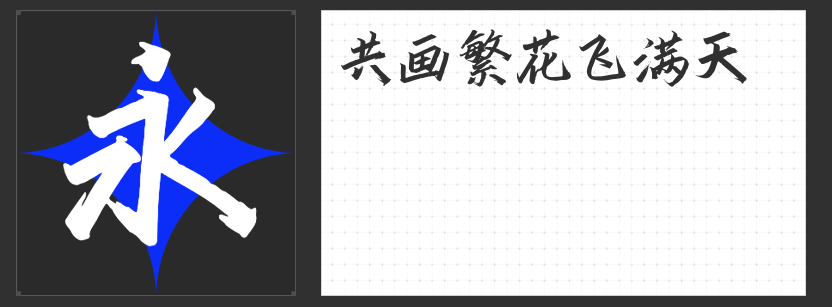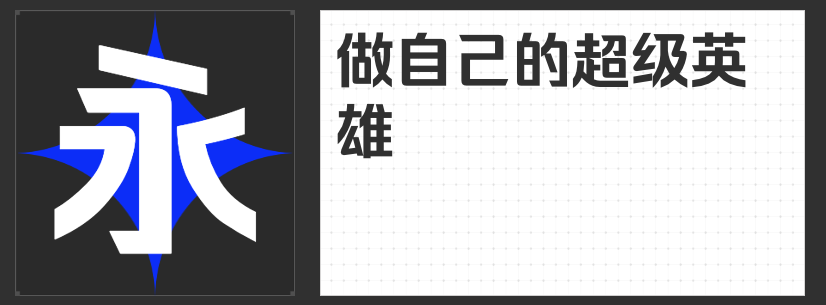
四款电商设计“吸睛利器”字体推荐~为设计施加视觉魔法
电商设计需在短短几秒内抓住用户注意力,字体作为视觉核心元素,直接影响品牌调性与转化率。本文精选四款风格迥异的商业字体,涵盖国风书法、现代黑体、实验性斜体及呆萌手绘风,助你轻松打造差异化视觉体验。
一、造字侠今朝醉简
这款毛笔楷书字体以“醉酒挥毫”为灵感,收笔处凌厉飞白,中锋用笔酣畅淋漓,字形结构正统却暗藏狂放。其笔画粗细对比强烈,横画如刀削斧凿,竖画似松柏挺立,尤其适合白酒、茶叶、文创等国风品类包装。
二、励字超级勇士简 大粗
突破传统黑体的刻板印象,这款字体通过“外方内圆”的笔画设计,在保持清晰易读性的同时,赋予字形柔和的亲和力。中宫适度收紧,字面率达92%,即使在小字号下仍能保持辨识度。
三、励字磅礴简 超黑
实验性采用“左斜右正”的矛盾结构,左侧笔画以15°倾斜制造动态张力,右侧垂直笔画则稳如磐石,形成“山峦叠嶂”的视觉冲击。该字体尤其适合运动品牌、汽车类电商。
四、励字憨憨简
以“婴儿手写体”为原型,所有笔画均采用圆弧过渡,字形如气球般饱满可爱。其装饰性极强却不显杂乱,特别适合母婴用品、零食、宠物用品等品类。
四款字体各具神通,覆盖电商设计从高端到年轻化的全场景需求。